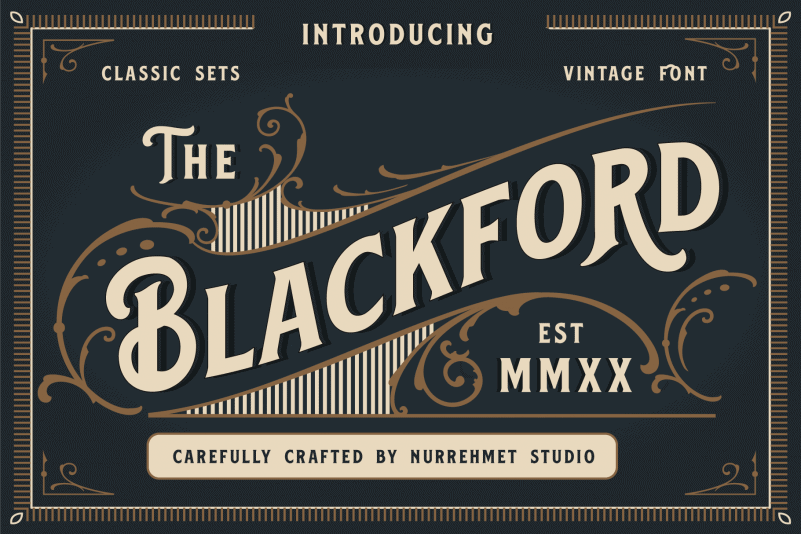
Blackford Display Font – Fonte Grátis
Blackford Display Font
A Blackford Display Font é uma nova fonte vintage inspirada nos velhos rótulos e embalagens, criando uma experiência de visualização única para qualquer projeto que você possa estar trabalhando. Esta fonte perfeitamente se adequa aos seus logotipos vintage, convites ou rótulos – um conjunto perfeito para combinar com outros detalhes vitorianos. A Blackford Display Font é ideal para criar letras em logo, headlines na revista ou projetos de qualquer tema retro. Ela traz uma atmosfera nostálgica e elegante que certamente deixará sua arte ou design surpreendente. Descubra a essência da fonte vintage nesse novo lançamento do Designer nurrehmetstudio.